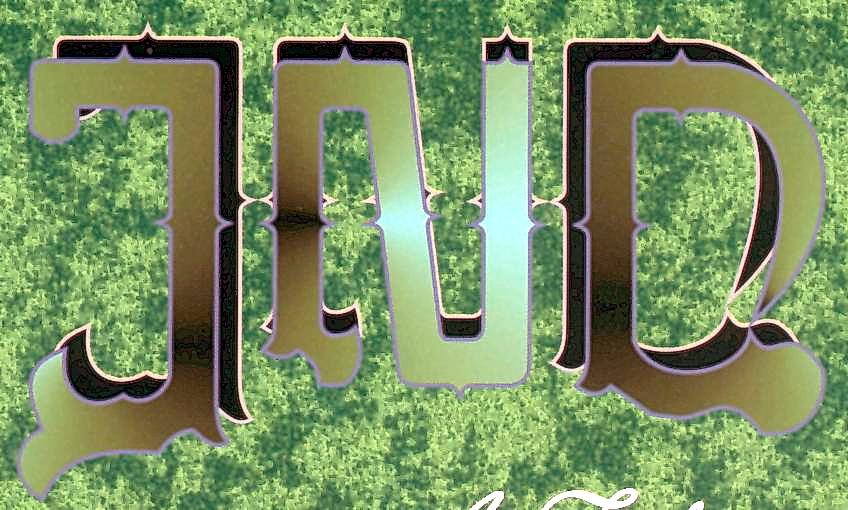
Eine Art Westernschrift
Ich suche eine Schrift für Band T-Shirts. Als Vorlage dient mir das Foto. Die Schrift könnte natürlich was selbst konstruiertes sein, aber dafür sieht sie mir zu professionell aus.
Könnt Ihr mir helfen?